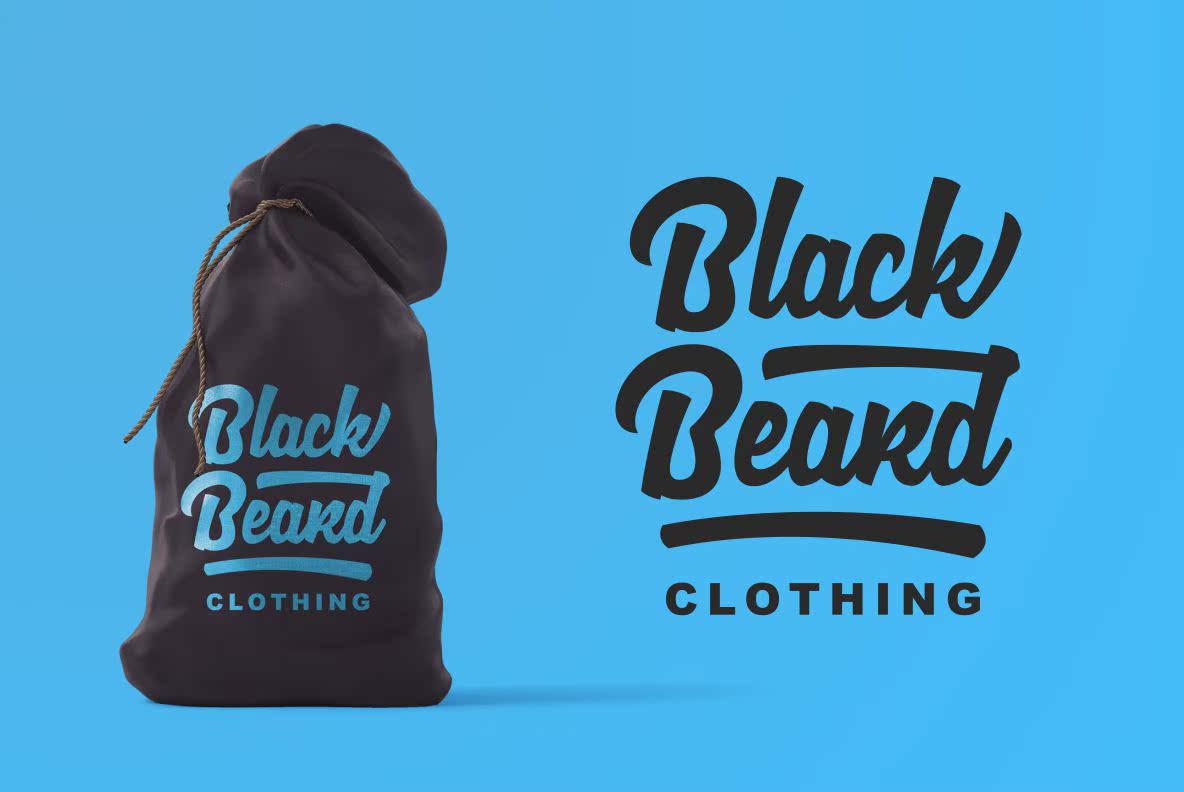
简介GournewProduct.LoguetownTypeface.AboldScriptFontInpired by BrushLettering.Perfectfordisplay、logotype、signage、Label和More。您可以将此Fonts应用于Modern和Vintage设计。简介GournewProduct.LoguetownTypeface.AboldScriptFontInpired by BrushLettering.Perfectfordisplay、logotype、signage、Label,labelandmore。您可以将此字体应用于现代和葡萄酒设计。